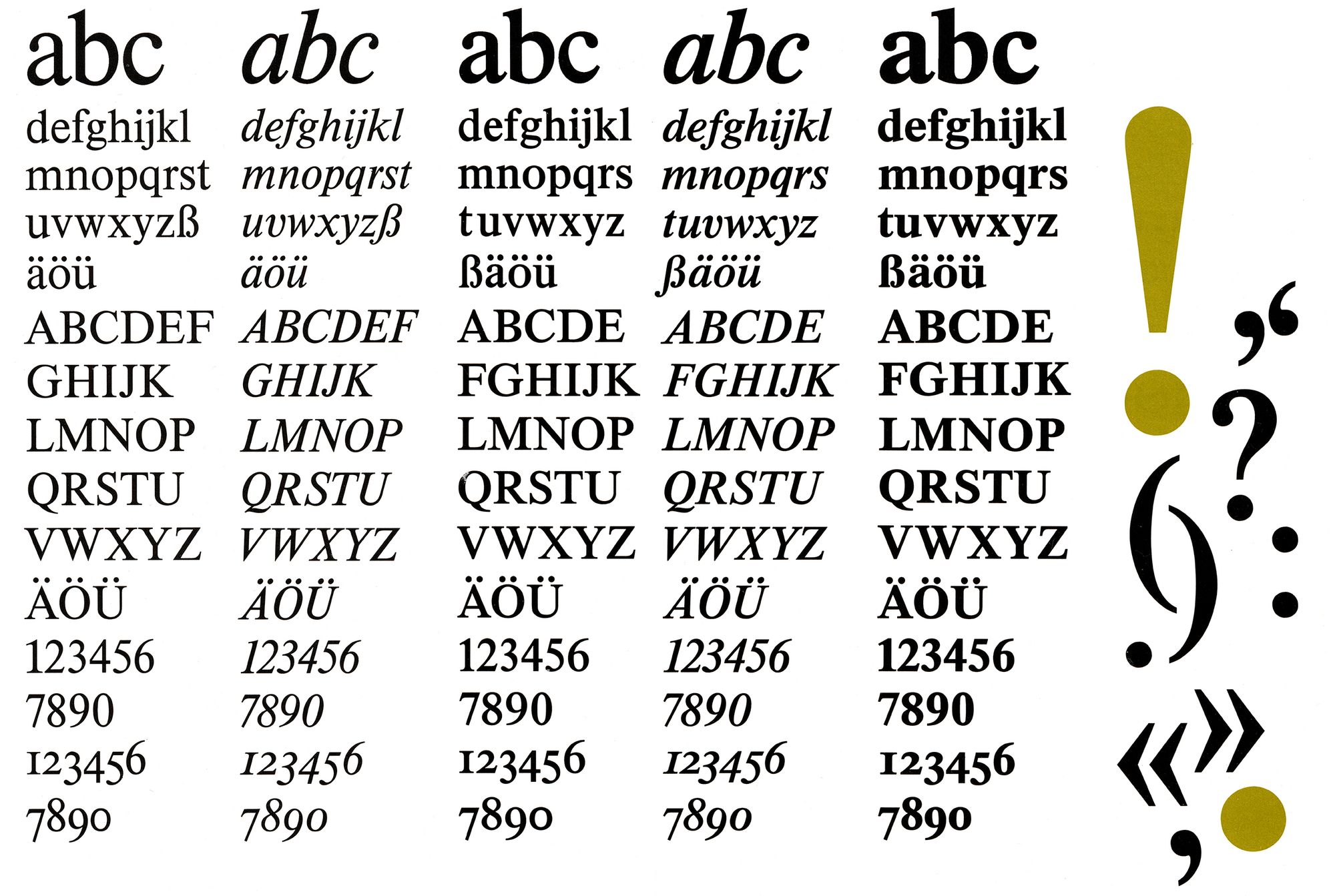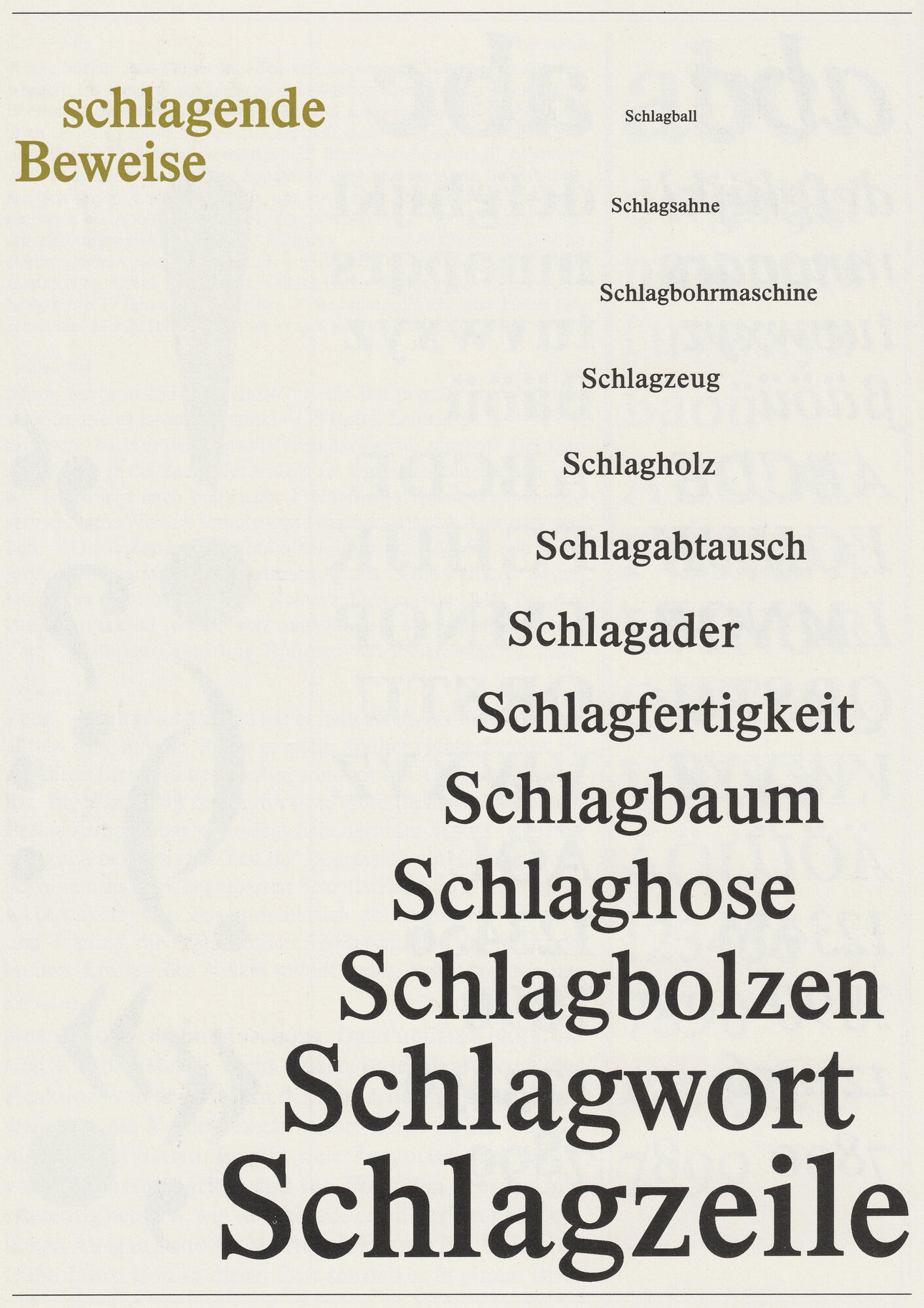
Die Timeless ist die ostdeutsche Bearbeitung der bekannten Zeitungsschrift Times. Die Timeless wurde von Werner Schulze gezeichnet und erschien in den 1980er-Jahren als Fotosatzschrift mit lateinischen, kyrillischen und griechischen Zeichen in mager, kursiv, halbfett, halbfett kursiv und fett.
Eine Digitalisierung auf Basis der Originaldaten erfolgte durch Elsner+Flake in drei optischen Größen (TB/TH/TI) und 6 Schnitten (TB/TH) bzw. 3 Schnitten (TI).